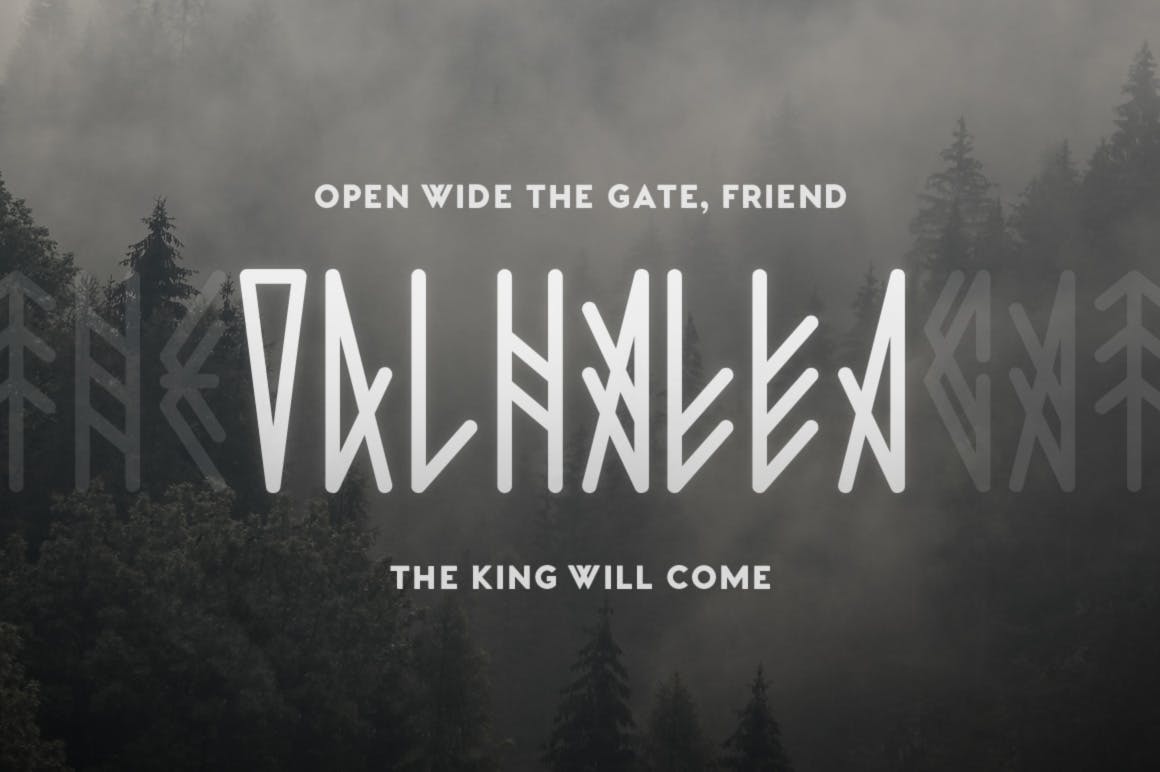
Jotunheim est une police inspirée des runes anciennes. Il propose trois versions différentes. La version 1 est le style le plus simple et le plus lisible. La version 2 est un peu plus complexe, ce qui ajoute plus d'authenticité au détriment de la lisibilité et la version 3 est le style le plus complexe.
Je recommanderais de mélanger les différentes versions pour obtenir des résultats uniques.
Jotunheim comprend des lettres majuscules multilingues, des chiffres et une ponctuation simple. Certaines lettres ont également des versions en miroir que vous pouvez basculer avec Caps Lock.